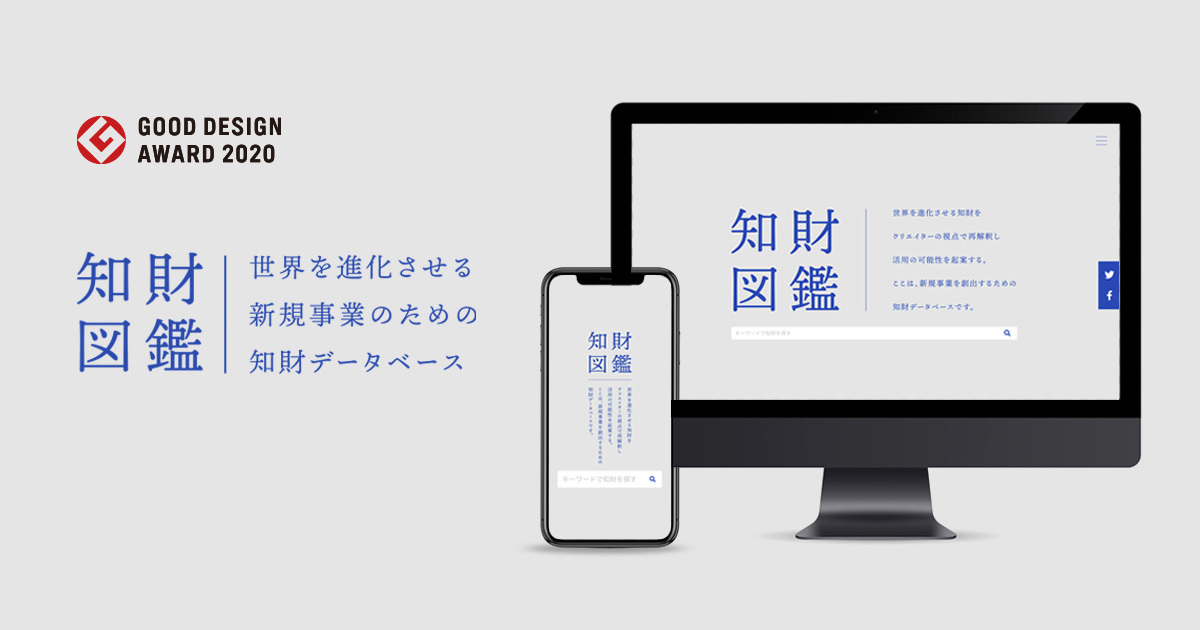
2020年度グッドデザイン賞を受賞した、オンライン知財データベース「知財図鑑」
知財図鑑により運営されるオンライン知財データベース「知財図鑑」が、公益財団法人日本デザイン振興会が主催する「2020年度グッドデザイン賞」を受賞した。
単に知財情報を紹介するだけでなく、社会に実装される活用方法を提示している点などを「知財への関心を高め、活用範囲を拡張する役割を果たした」として評価された。
知財図鑑とは
世界を進化させる可能性のある「すごい知財」に出会えるデータベースです。網羅性を重視した一般的な図鑑とは違い、新規事業への活用案をクリエイターが提案することを特徴としており、特許技術だけでなく、プロダクトやサービスから実用的なAPIまで、広義の「知的財産」を対象に編集を進めている。
「知財図鑑」は、新規事業を創出することを目的とした、オンライン知財プラットフォーム。企業間の知財マッチングを促進するため、活用シーンを高解像度にビジュアライズする「妄想プロジェクト」や、知財説明会のオンライン配信などを実施してきた。
今回、知財図鑑が受賞したのはグッドデザイン賞の「産業向け意識改善・マネジメント・取り組み」カテゴリーとなり、バイアスにとらわれず、知財の活用シーンをクリエイターが考えるなど、これまでの知財プラットフォームには見られない取り組みの新規性やインターフェイスのデザイン性の高さが評価の対象となった。
厳重に保護されていることが多い「知財」を一定の権利保護の下、幅広いユーザーへの利用を促進することにより、新たな知財活用のアイディアや新規事業プランが生み出されることを目的として知財図鑑は誕生した。
その際、単に知財の技術側面を紹介するだけにとどまらず、応用が有効な分野や事業アイディアをセットで紹介し、知財がもたらす「理想の未来像」を描くことで知財の可能性を拡張してきた。
知財図鑑は元々、クリエイティブ制作を主体とする株式会社コネルが母体となっていることもあり、様々なジャンルのクリエイターが「知財ハンター」として知財を探し、活用方法を妄想してきた。そうした研究者ではない、生活者の目線で知財をとらえていることが「知財への関心を高め、活用範囲を拡張する役割を果たした」という評価につながった。
▼審査委員による「知財図鑑」評価コメント
単に特許の概要やポイントを紹介するだけでなく、社会に実装され、活用されることを意識してつくられている。個々の知財の価値を、具体的な活用ビジョンや将来像も含めて紹介することで、知財への関心を高め、活用範囲を拡張する役割を果たした。
思わず使いたくなるような見やすさと興味深い内容、インターフェイスの工夫も素晴らしい。休眠特許を掘り起こしなど、具体的な成果も出ている。今後、知財活用のプラットフォームとして定着し、多くのクリエイティブの誘発につながることを期待したい。
「知財図鑑」クリエイティブディレクター:宮田大氏
コネルのクリエイティブディレクター・宮田大がブランドデザインを統括し、「知財業界において異端である」ことを意識したデザインを設計。「イメージビジュアルや未来を感じさせるイラストを使用し、活用方法のアイディアを湧きやすくしている」ことで、大手企業とのコラボレーションなど具体的な成果につながっている。今後も知財図鑑では、クリエイティブの強みを活かした知財活用に関するブランディングやコンサルティング、マッチング事業を推進していく。
「貂明朝」採用など、オンライン知財データベース「知財図鑑」デザインコンセプト
「知財」のイメージとして「取得しておかないと、競合他社にアイディアを奪われる」といったような「守り」のイメージがある。知財図鑑では「守り」から「知財を活用して、生かしていく」といった「攻め」のイメージを新たに付加できるように、現状の知財業界では見られないような「フラットかつ、グラフィカルな要素の強い」デザインを心がけ「知財界の異端」を目指した。
ただ、従来の知財の「スマート」「知的」というイメージは踏襲させるために、装飾を極力ひかえて合理的でシンプルなデザインにした。また「図鑑」の名の通り、検索しやすいUIや検索したいビジュアルになるよう心がけた。
例えばVIでは、インテリジェントな図鑑として前記のような「異端児感」を目指すために「箱組み」で構成し、フォントは強めで有機質の残る「貂明朝」を基本に採用した。
WEBサイト自体もそのトーン&マナーを引き継いで構築した。